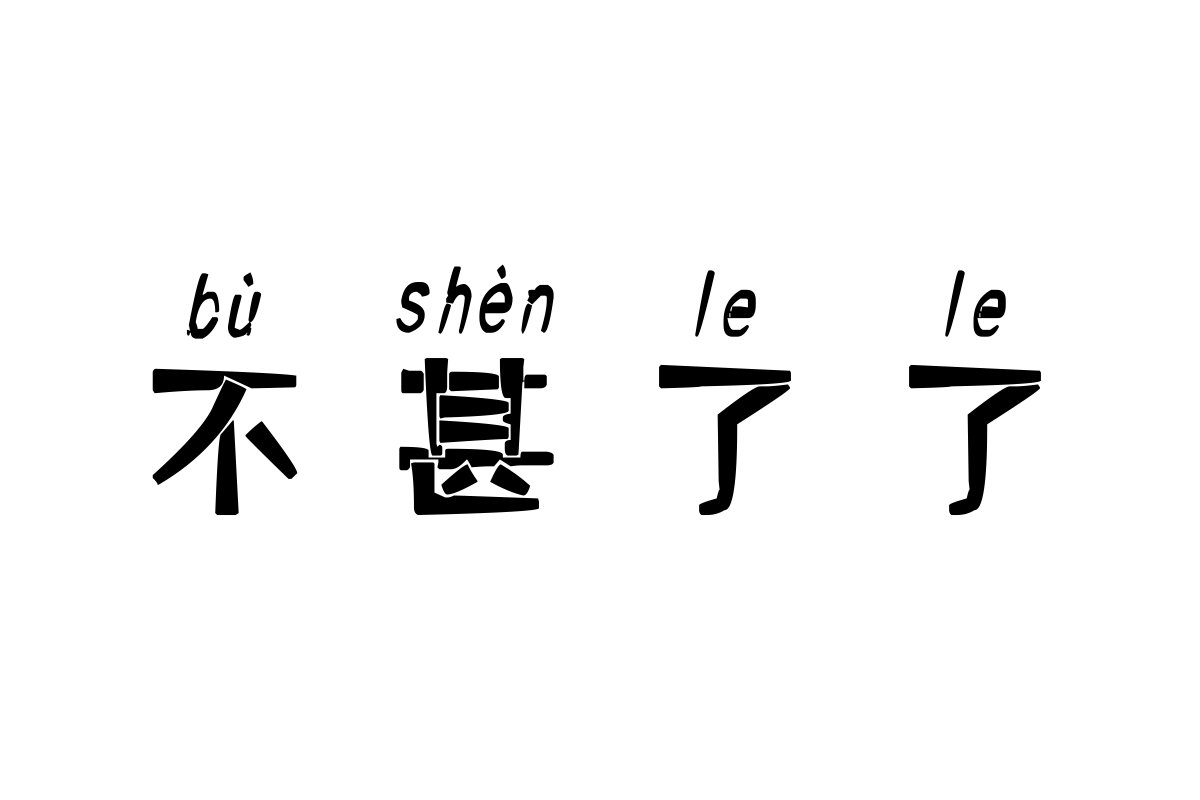
汉标赵黑拼音是一款具有独特风格的中文字体,由汉标字库公司设计。这款字体以其独特的字形和风格吸引了众多用户的关注。
汉标赵黑拼音的字形结构简洁明了,笔画流畅自然。它的每个字符都经过精心设计,使其在视觉上呈现出独特的美感。同时,这款字体也注重易读性,使得阅读起来更加方便。
此外,汉标赵黑拼音还具有丰富的应用场景。无论是在网页设计、广告制作还是其他需要展示文字的地方,这款字体都能展现出其独特的魅力。用户可以根据自己的需求选择不同的字形样式,以满足各种场景的需求。
总之,汉标赵黑拼音是一款值得推荐的中文字体。它以其独特的风格和易用性,为用户带来了更好的视觉体验。